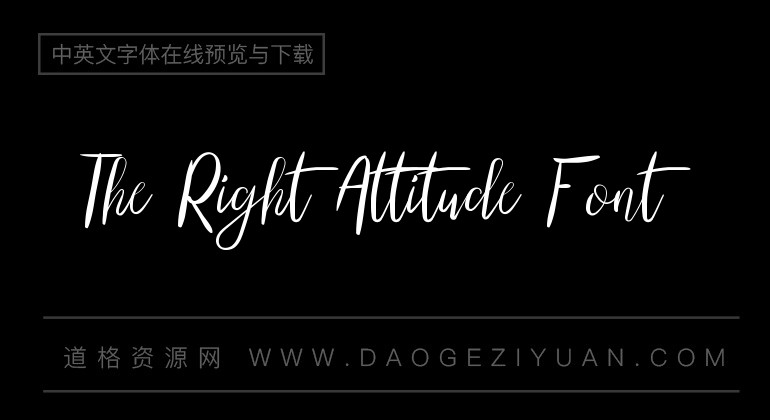
The Right Attitude Font
The Right Attitude是一种现代化的手写风格字体,具有非常自然的笔画和独特的个性。 该字体由设计师Måns Grebäck创建,可用于商业和非商业用途。它的字母形态非常流畅,具有良好的可读性和视觉吸引力。字母之间的间距很好地平衡,使其易于阅读和使用。 The Right Attitude字体提供多种字形和大小,可以适应不同的设计需求,例如标志、海报和书籍封面等。此外,该字体还支持多种语言,包括英语、法语、西班牙语、德语、意大利语和葡萄牙语等,因此可以应用于各种不同的设计项目中。
The Right Attitude Font是一款非常不错的手写艺术字体,具有很好的视觉感,适合于文化类的宣传设计、商业类品牌的广告和产品包装设计以及个性化文字排版等较多场景。